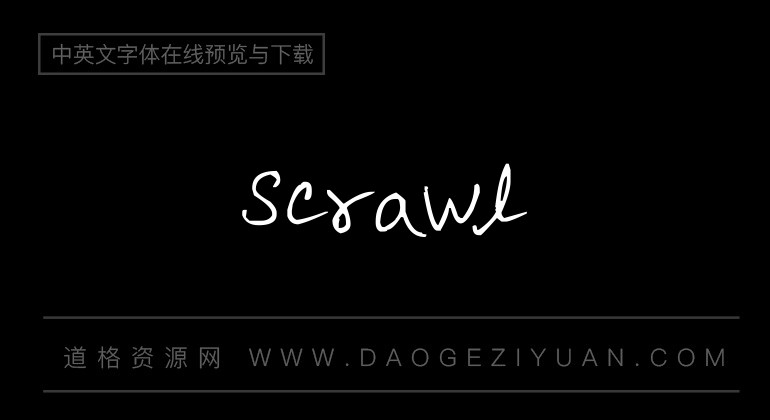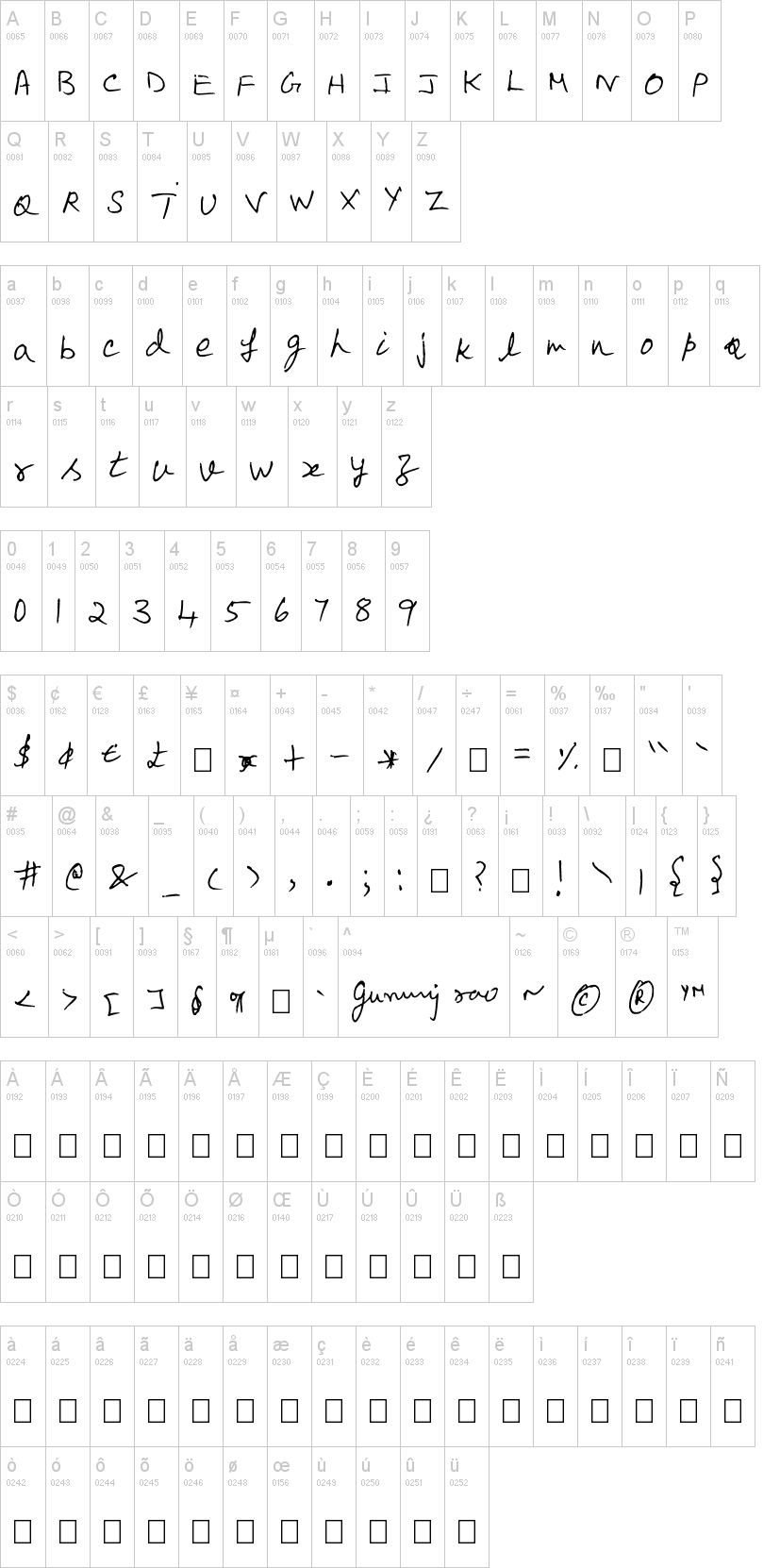
Scrawl
Scrawl 字体是一款拥有独特设计风格的手写体字体。它拥有粗犷、朴实的外观,可以让文字充满活力和个性。Scrawl 字体可以用于拼写单词、标题、标签等,也可以用于设计海报、标语、网页等,可以让你的设计更加有趣和生动。
Scrawl是一款非常不错的手写艺术字体,具有很好的视觉感,适合于文化类的宣传设计、商业类品牌的广告和产品包装设计以及个性化文字排版等较多场景。
Scrawl字符映射图